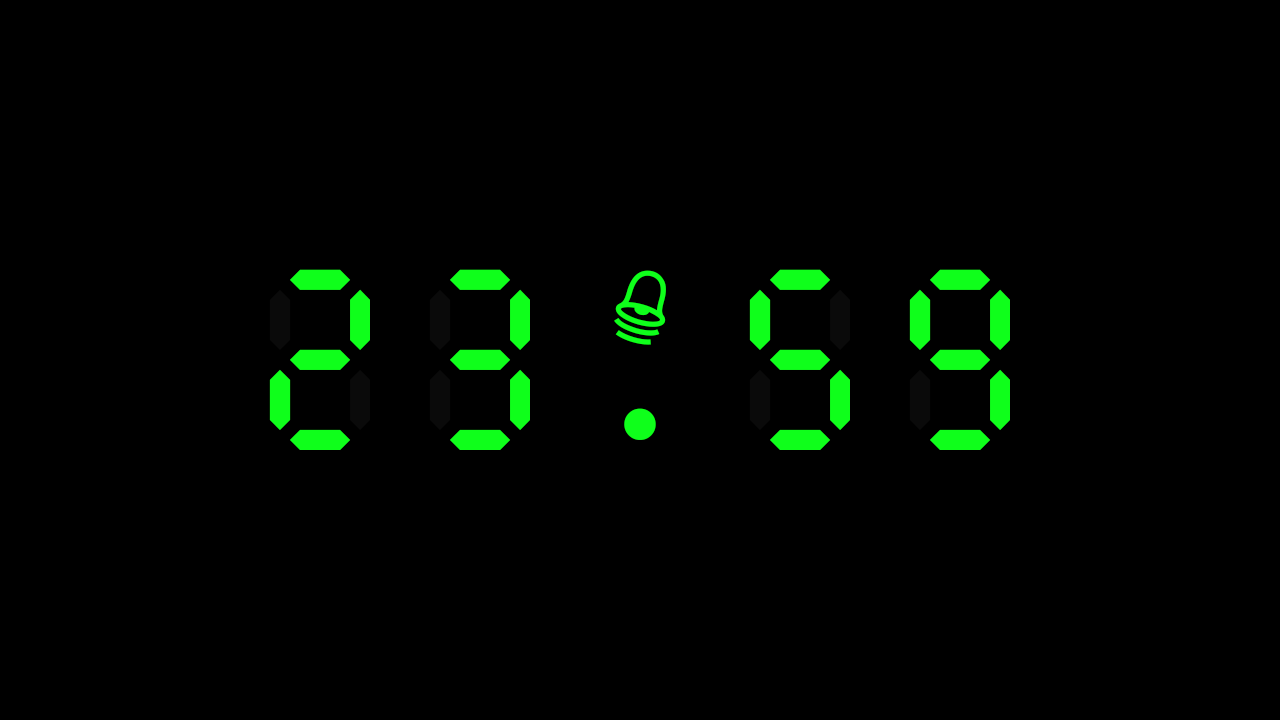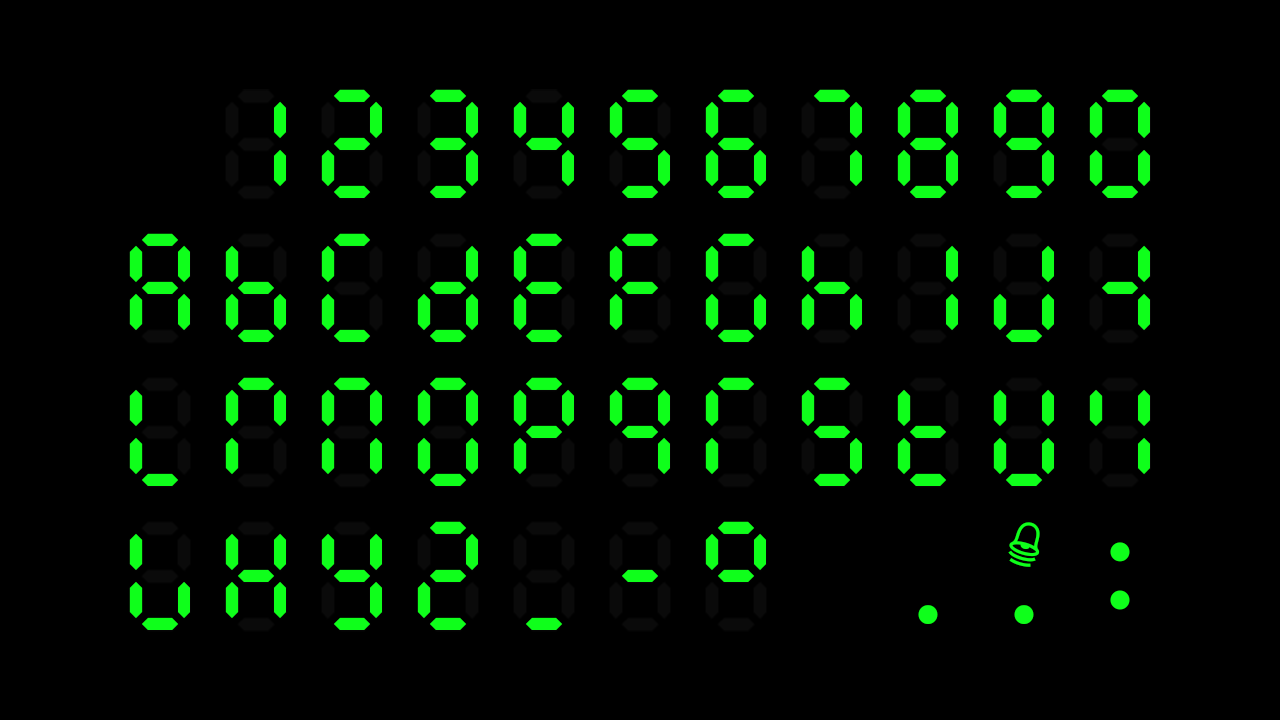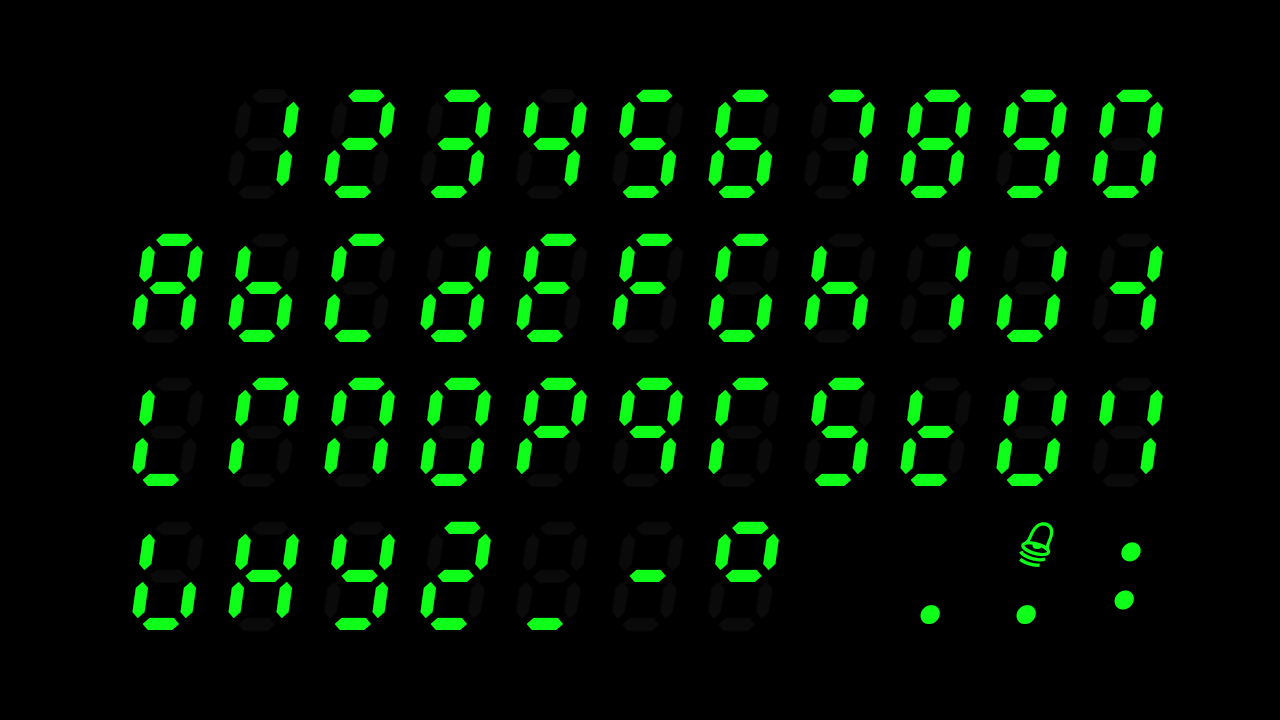
E1234 是一款设计灵感源于电子闹钟或早期数字显示屏的免费开源英文字体,以其独特的数码风格和广泛的语言支持为特点。其设计模仿了七段数码管或电子时钟的显示效果,字符由简洁的直线段构成,形成鲜明的几何图形感。
字体家族包含 Regular(常规) 和 Italic(斜体) 两种样式,共计115个字形。覆盖了包括英语、印尼语、索马里语、斯瓦希里语、祖鲁语在内的34种使用拉丁字母的语言。
字体风格
E1234 的风格是“功能主义的数码复古”。它精准地捕捉了20世纪七八十年代电子设备上那种由离散发光线段构成的字符美学,充满了特定的时代科技感。所有字母和数字均由标准的横、竖线段拼接而成,转角尖锐,笔画间距均匀,形成一种高度理性、模块化且略带机械冷感的视觉形象。
Italic 样式并非传统的手写倾斜,而是整个模块化结构在轴向上进行的有规律偏转,保持了风格的统一。